问号
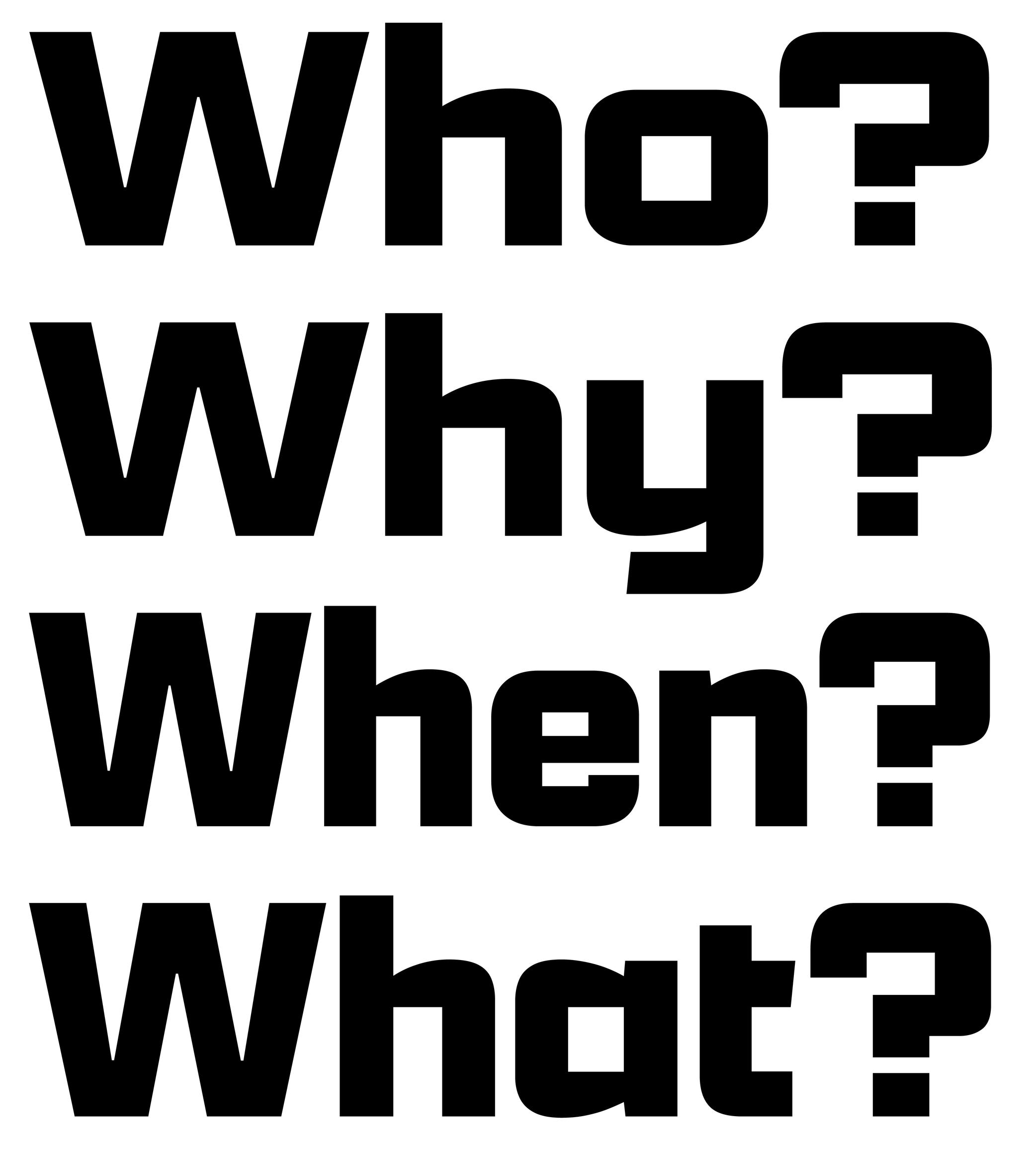
赞助者:Kerns & Cairns 。字体:Apotek 。设计师:Dyana Weissman。2020年出版。
问号位于问句的末尾。
在 16 世纪的拉丁文本中,问号用字母 Q 标在 o 的上方(拉丁文中 quaestio “问题” 的缩写)。经过几个世纪的演变,它变成了我们今天所知的简化形式。
问号在文本中必须有足够的存在感,以便能很快被看到。在拉丁文中,问号的高度和宽度与大写字母大致相同。问号的设计必须与字体中的其他字形相关联,其中上方的末端与字体中其他字形的末端相关联(如 2、f 或 C),下方的点与句号相同。
在英语和所有其他基于拉丁文字的语言中,问号前是没有空格的,唯有法语例外,问号前有一个不间断的细空格。
在西班牙语中,反向问号位于问题的开头,正向问号位于问题的结尾,且问号和单词之间没有空格。